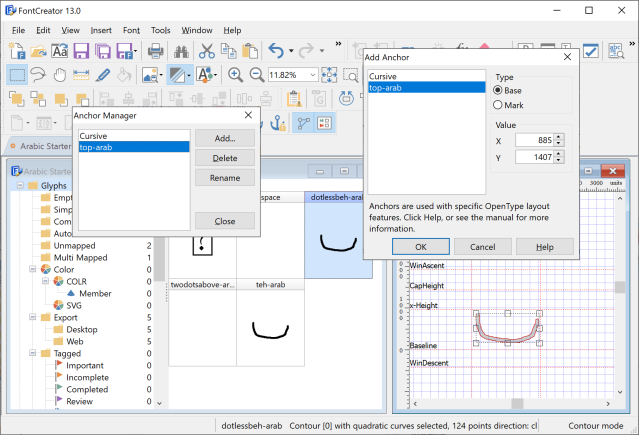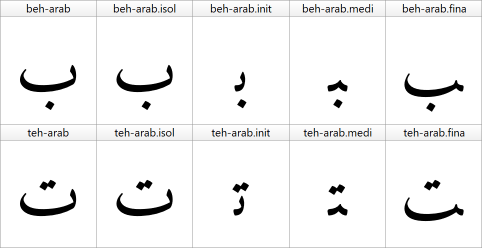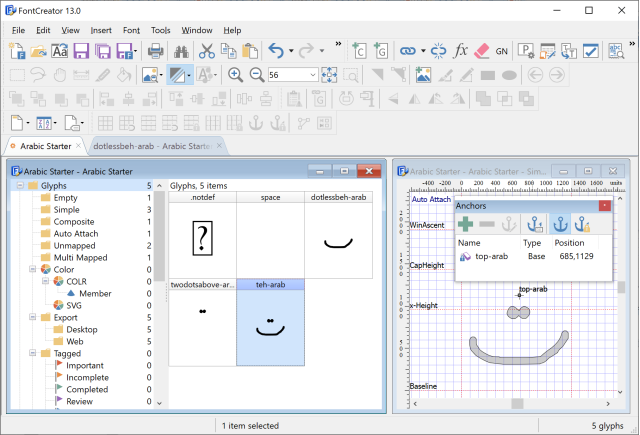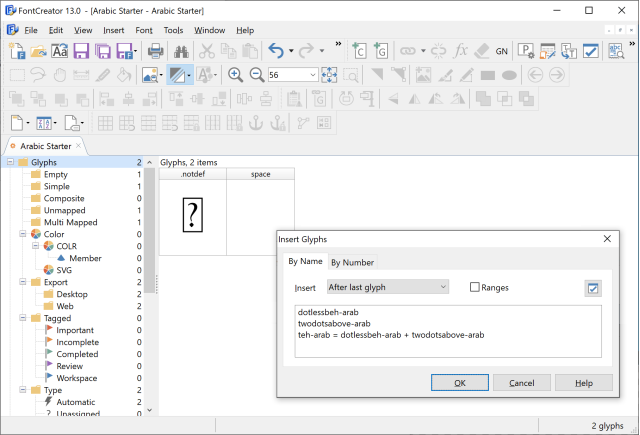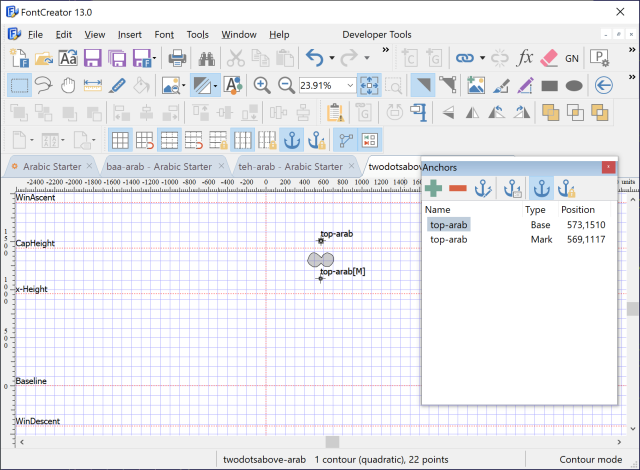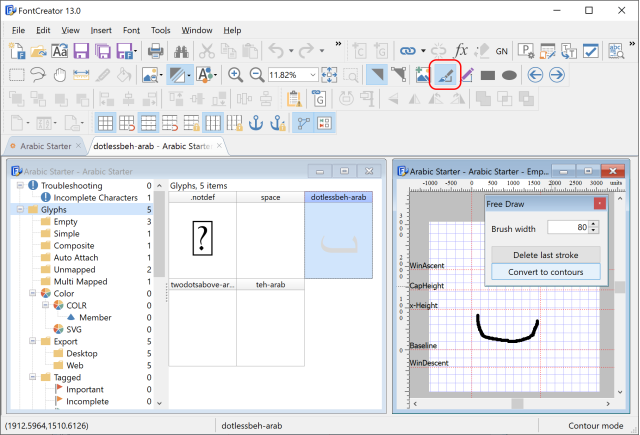
FontCreator 提供了阿拉伯文字型開發所需的高階工具,覆蓋阿拉伯文、波斯文、馬來文、信德文、維吾爾文與烏爾都文。本教程介紹製作專業級阿拉伯文字型所需的若干進階主題。
本教程針對 FontCreator,但它提供了許多可用於其他字型編輯器的資訊。FontCreator 像任何其他字型編輯器一樣,主要用於設計基於拉丁文的字型,但我們的字型編輯器還配備了開發阿拉伯字型所需的高階工具,涵蓋阿拉伯語、波斯語、馬來語、信德語、維吾爾語和烏爾都語。OpenType 設計器以及我們的原生形狀引擎和互動式 OpenType 佈局校對允許您建立、編輯和測試複雜指令碼字型。
由於大多數阿拉伯字元連線,視覺外觀取決於字元上下文。通常字母有四種上下文形式:
在非連線上下文中,使用孤立形式。初始形式用作連線字母組的起始,最後一個字母使用最終形式,中間的所有字元使用中間字元形式。
由於大多數阿拉伯字母具有所有四種形式,因此需要許多字元和字形。幸運的是,許多字形可以使用其他字形的輪廓,FontCreator 可以幫助使用複合字形和錨點生成它們。
我們現在建立一個新字型,Arabic Starter。
新字型附帶超過 200 個(主要是拉丁文)字元。通常您希望保留這些字元,但為了簡單起見,我們刪除除前兩個之外的所有字元,並手動新增一些阿拉伯字母。
FontCreator 使用智慧字形命名,因此如果您知道名稱,可以快速將它們新增到字型中。我們使用插入字形視窗新增 teh-arab,這是孤立形式。由於我們希望它使用其他字形,我們也新增這些字形。確保未選中範圍,因為這會與包含連字元的字形名稱衝突。
dotlessbeh-arab twodotsabove-arab teh-arab = dotlessbeh-arab + twodotsabove-arab
我們現在向字形新增輪廓。單擊自由繪製圖示以快速繪製輪廓。還有其他製作和細化它的方法,但對於本教程,我們採用簡單的方法。
當您對結果滿意時,單擊轉換為輪廓按鈕。您可能希望透過單擊並拖動最右側的垂直虛線來更改右側字距。當我們仍在字形編輯視窗中時,我們開啟錨點管理器(可從字型選單訪問)並新增一個名為 top-arab 的新錨點類。此類現在可用於定義頂部錨點標記,以在基礎字形上定位標記。
仍在字形編輯視窗中,我們在 dotlessbeh-arab 輪廓上方右鍵單擊並選擇新增錨點…以新增基礎錨點。
現在您可以單擊並移動錨點以將其重新定位到您喜歡的位置,滿意時關閉此字形編輯視窗。
在字型概覽視窗中,雙擊字形 twodotsabove-arab 以在字形編輯視窗中編輯它,並使用自由繪製製作輪廓。
此字形將用作標記,因此在輪廓下方稍右鍵單擊以新增標記錨點。由於其他標記可以放置在此標記之上,我們還在輪廓上方新增基礎錨點。因此,您最終同時擁有基礎錨點和標記錨點。
現在您可以關閉此視窗,如果一切順利,您應該對目前的結果感到滿意,因為 teh-arab 現在也已完成!
這是一個很好的開始,它允許我們為 teh-arab 新增其他字元形式。我們再次轉到插入字形視窗。我們首先插入無點變體,因為它們將用於製作字元形式:
dotlessbeh-arab.init dotlessbeh-arab.medi dotlessbeh-arab.fina teh-arab.init = dotlessbeh-arab.init + twodotsabove-arab teh-arab.medi = dotlessbeh-arab.medi + twodotsabove-arab teh-arab.fina = dotlessbeh-arab.fina + twodotsabove-arab
現在向前三個(無點 beh 形式)新增輪廓,不要忘記向它們新增基礎錨點。
待續...